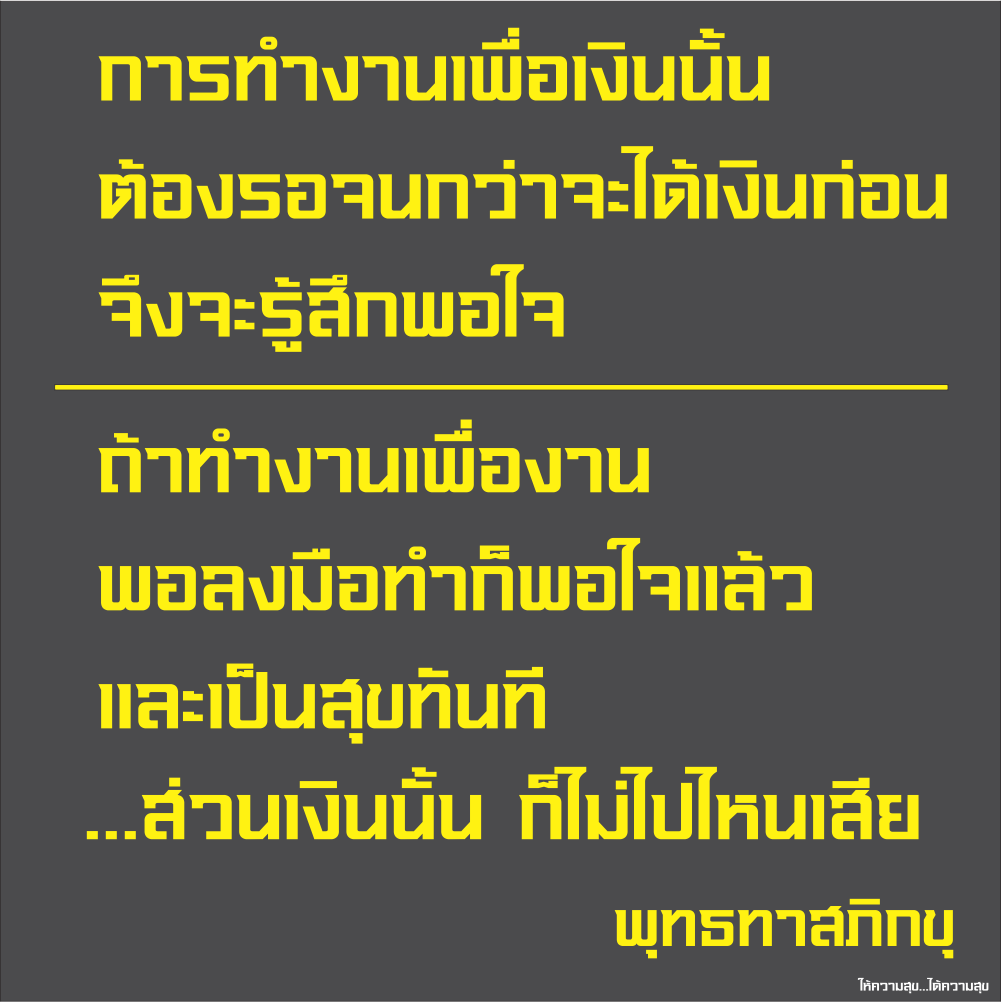
เอสดี โปรโตไทป์ (sd prototype)
เอสดีโปรโตไทป์ เป็นฟอนต์ออกแนวกึ่งทางการ เหมาะสำหรับพาดหัวต่างๆ ทำไว้นานแล้วตอนช่วงโควิดระบาด  ไม่ได้ไปไหนเลยขึ้นแบบลายเส้นไว้